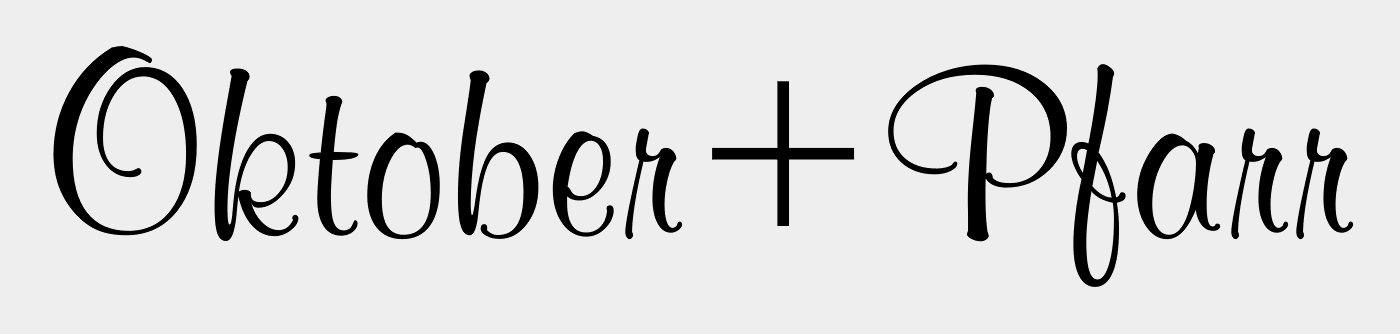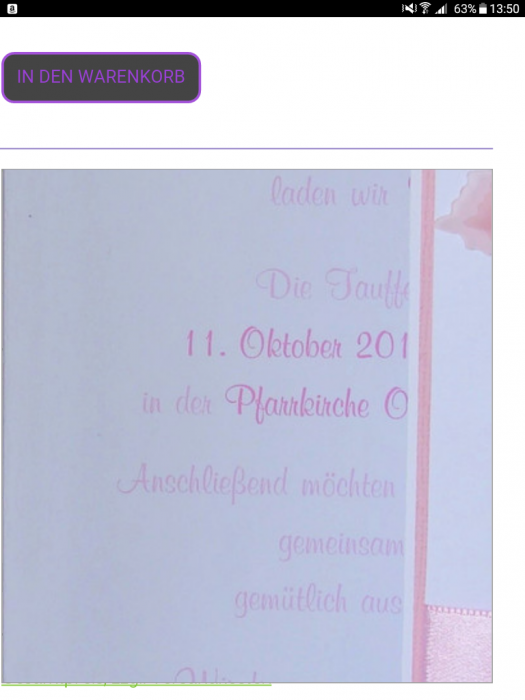
Suche 2.te schrift für Taufeinladung
Hallo Leute, da Ihr mir heute morgen so schnell geholfen habt, wende ich mich nochmal an euch was diese Schriftart angeht:) vielen Dank im voraus :)
Muss es diese Schriftart sein? Wenn du nur diesen Schreibstil suchst, bist du auch bestens bedient mit  den Schriften von Laura Worthington. Sie ist die Königin in dieser Disziplin! Ihre Schriften haben meistens auch unzähliche Opentype-Features, sodass du für jeden Buchstaben etliche Alternativen hast.